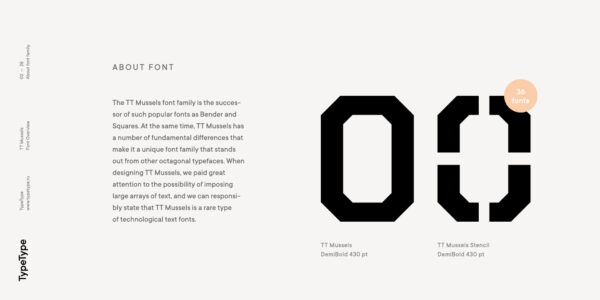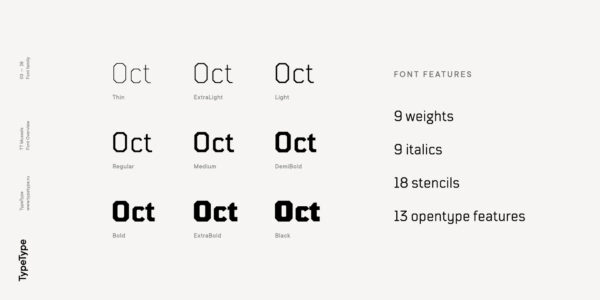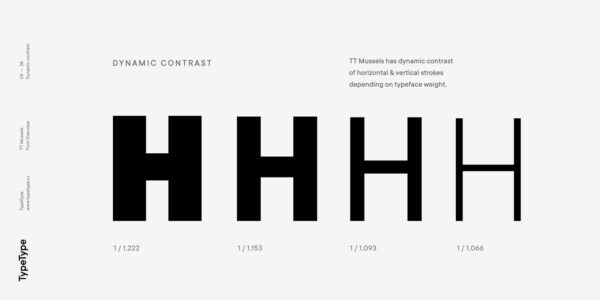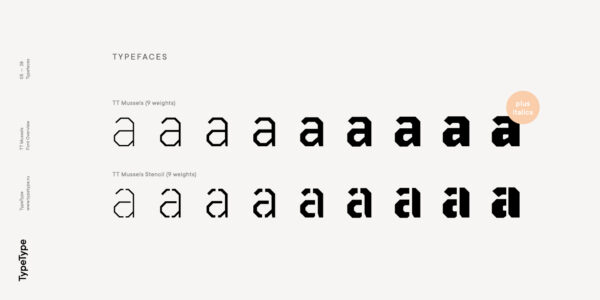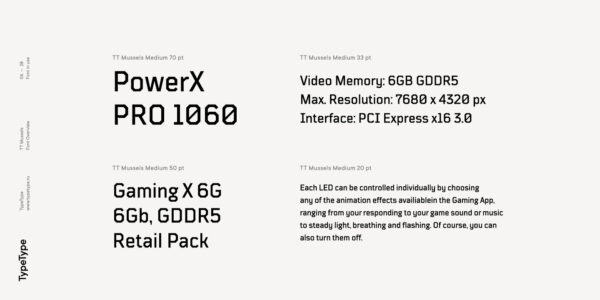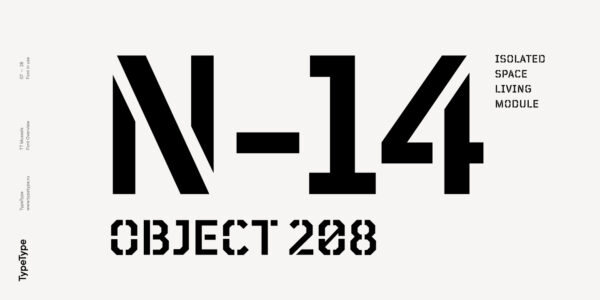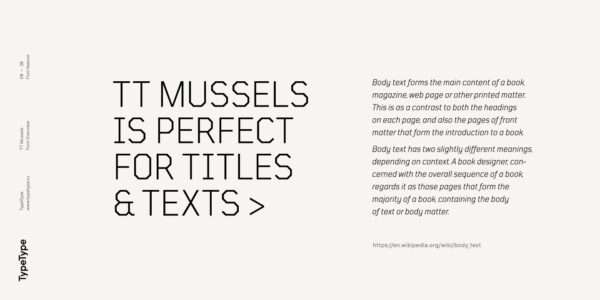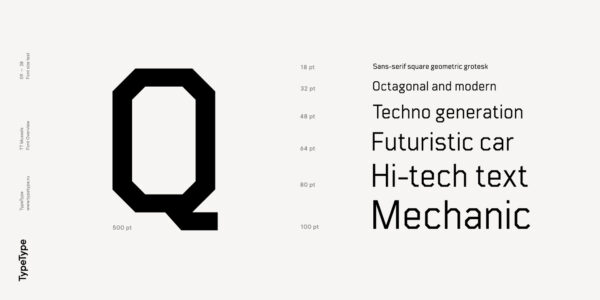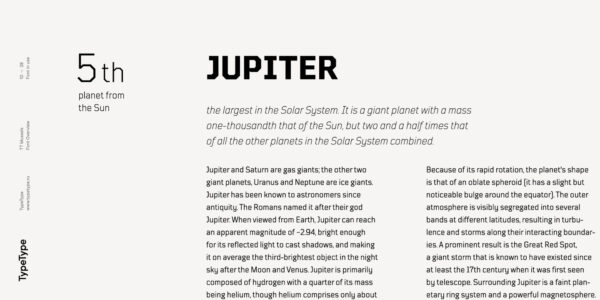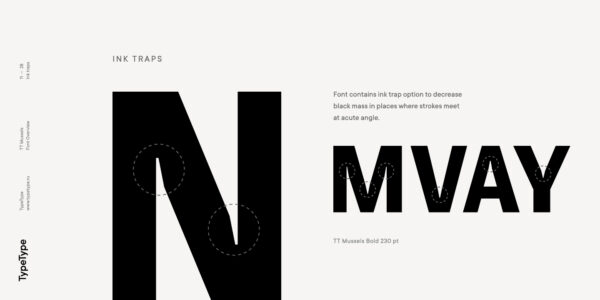
TT Mussels
TT Mussels — ТТ Масселс
Произносится «ТТ Масселс». «Mussels» — производное слово от mussel, в переводе с английского «мидия». Буквы «TT» являются аббревиатурой названия компании.
TT Mussels — октогональный текстовый шрифт с технологическим акцентом. В гарнитуру входит эффектная трафаретная версия.
Редкий вид технологичных текстовых шрифтов
В дизайне TT Mussels можно найти знаки уважения традиционным текстовым шрифтам — след движения пером исторически свойственный антиквам. На примере буквы М из Black начертания мы можем увидеть сначала тонкий штрих, потом диагональный толстый штрих, следом диагональный тонкий штрих и завершающий вертикальный жирный штрих. Этот эффект постепенно исчезает при приближении к тонкому начертанию.
TT Mussels — уникальное семействое, сильно выделяющееся среди октогональных гарнитур
В TT Mussels широко используется динамический контраст
О гарнитуре TT Mussels
Шрифтовая гарнитура TT Mussels является правопреемником таких популярных шрифтов как Bender и TT Squares. При этом в TT Mussels есть ряд фундаментальных отличий, которые делают его уникальным семейством, сильно выделяющимся среди октогональных гарнитур. При проектировании TT Mussels мы уделили большое внимание возможности верстать большие массивы текста и можем ответственно заявить, что TT Mussels является редким видом технологических текстовых шрифтов. Ко всему прочему мы изготовили трафаретную версию гарнитуры, в которой расположение надрезов меняется исходя их толщины начертания. В общей сумме шрифтовое семейство TT Mussels состоит из 36 начертаний, в состав которых кроме всего прочего входят стилистические альтернативы, лигатуры, а также большая поддержка OT фич: case, frac, ordn, sups, sinf, numr, dnom, onum, tnum, pnum, liga, dlig, salt, ss01.
В TT Mussels широко используется динамический контраст, который максимально заметен в Black начертании, где отношение толщины вертикальных штрихов к горизонтальным штрихам равняется примерно двум к одному. Приближаясь к Thin начертанию толщина вертикальных штрихов уже соответствует толщине горизонтальных штрихов. В дизайне TT Mussels можно найти и другие знаки уважения традиционным текстовым шрифтам—след движения пером исторически свойственный антиквам. На примере буквы М из Black начертания мы можем увидеть сначала тонкий штрих, потом диагональный толстый штрих, следом диагональный тонкий штрих и завершающий вертикальный жирный штрих. Как и в случае с динамическим контрастом, этот эффект постепенно исчезает при приближении к тонкому начертанию. В жирных начертаниях в таких местах как «подмышки» букв MNИ, а также в местах соединения диагоналей WVvw присутствуют визуальные компенсаторы, которые осветляют жирные начертания. По мере движения толщин начертаний от жирных к тонким, размеры и концептуальное значения компенсаторов меняется и в тонких начертаниях они совсем исчезают.
Basic Latin Basic Cyrillic Extended Latin Stylistic Alternates, Standard and Discretionary Ligatures|salt,liga,dlig Lining Figures, Currencies Old-style Figures|onum Punctuation, Symbols, Mathematical Symbols, Arrows
salt | Stylistic Alternates
aygJ
liga | Standard Ligatures
ff fl fi
dlig | Discretionary Ligatures
ch st
onum | Oldstyle Figures
1638
case | Case Sensitive Forms
({[H]})
frac | Fractions
1/2 3/4